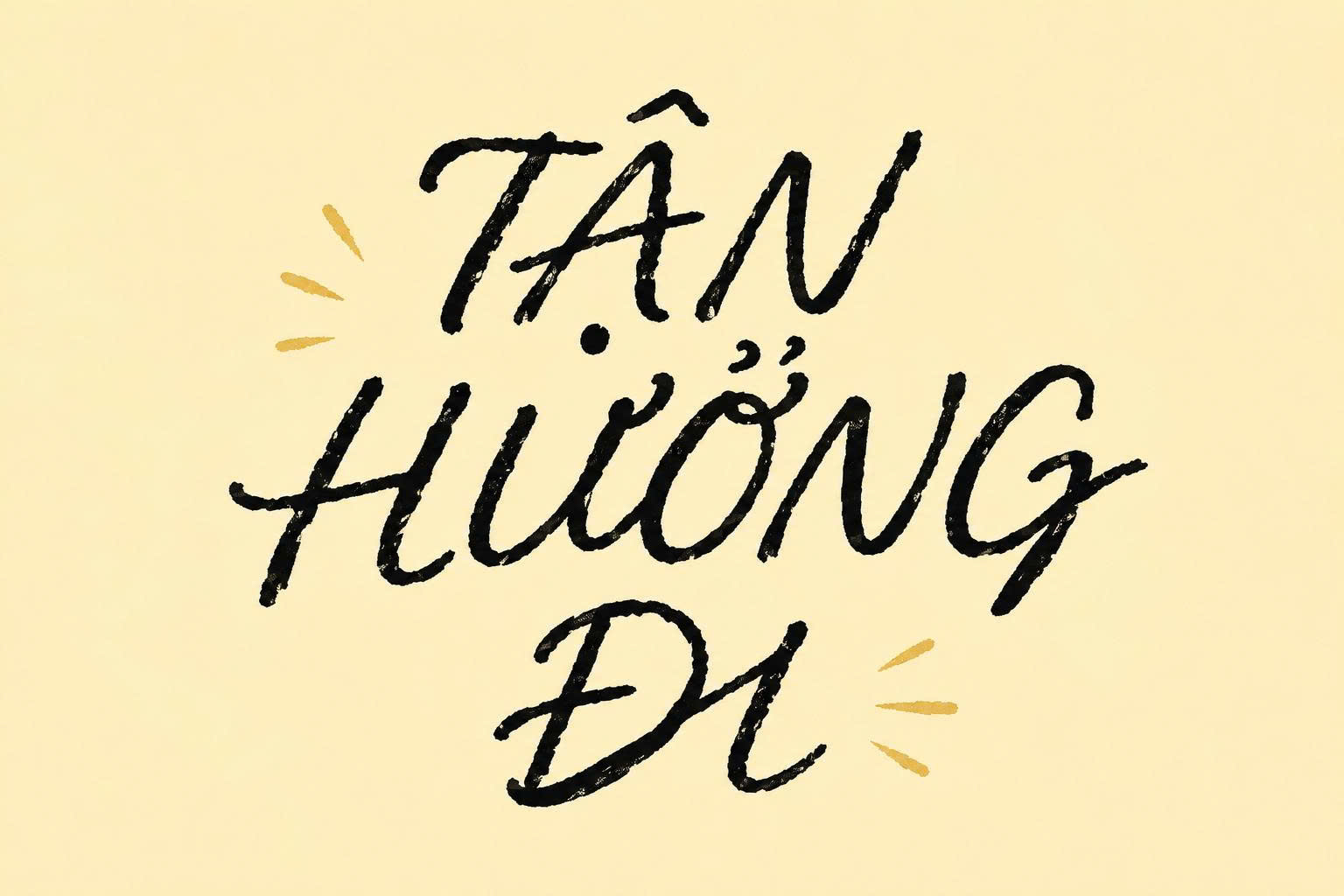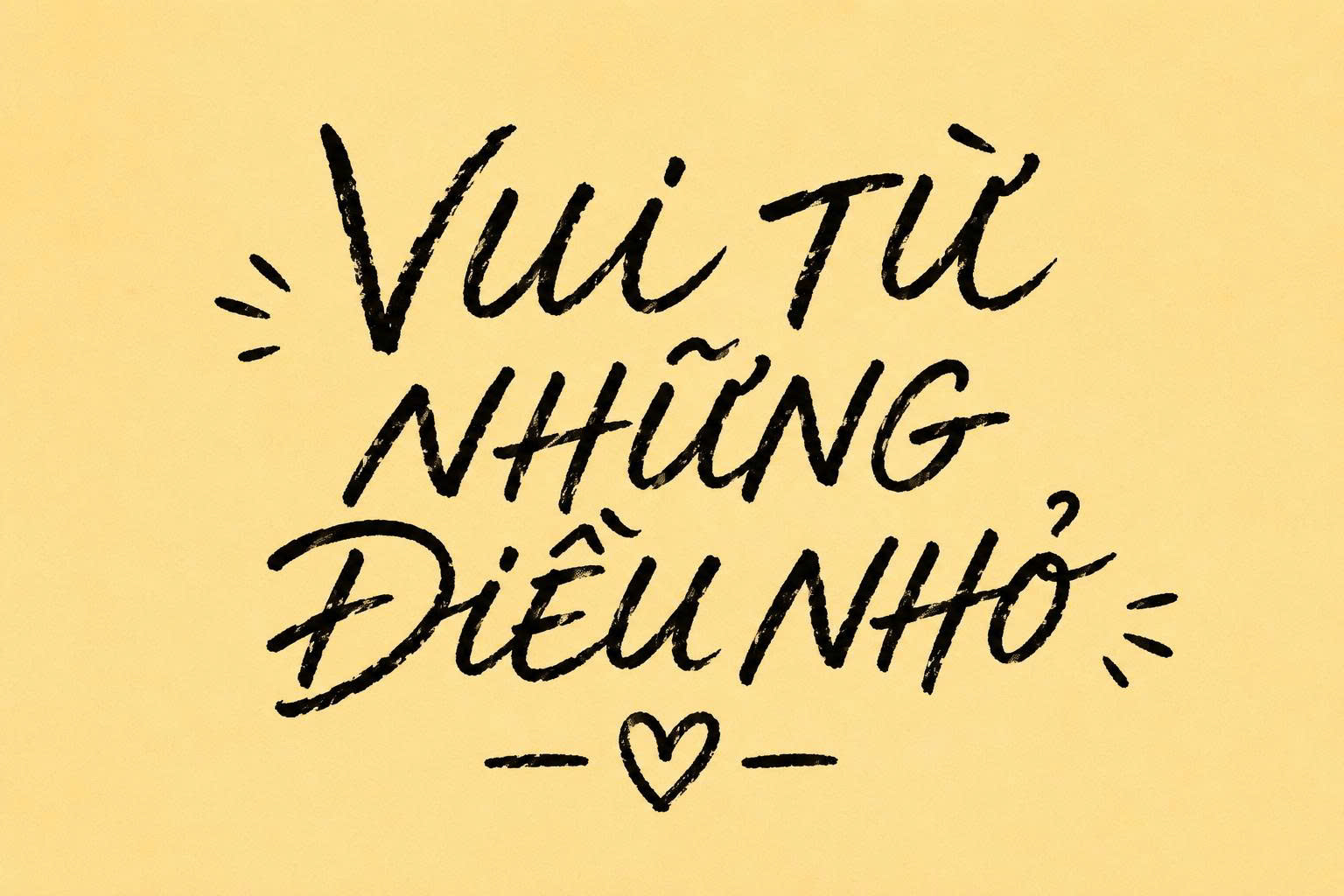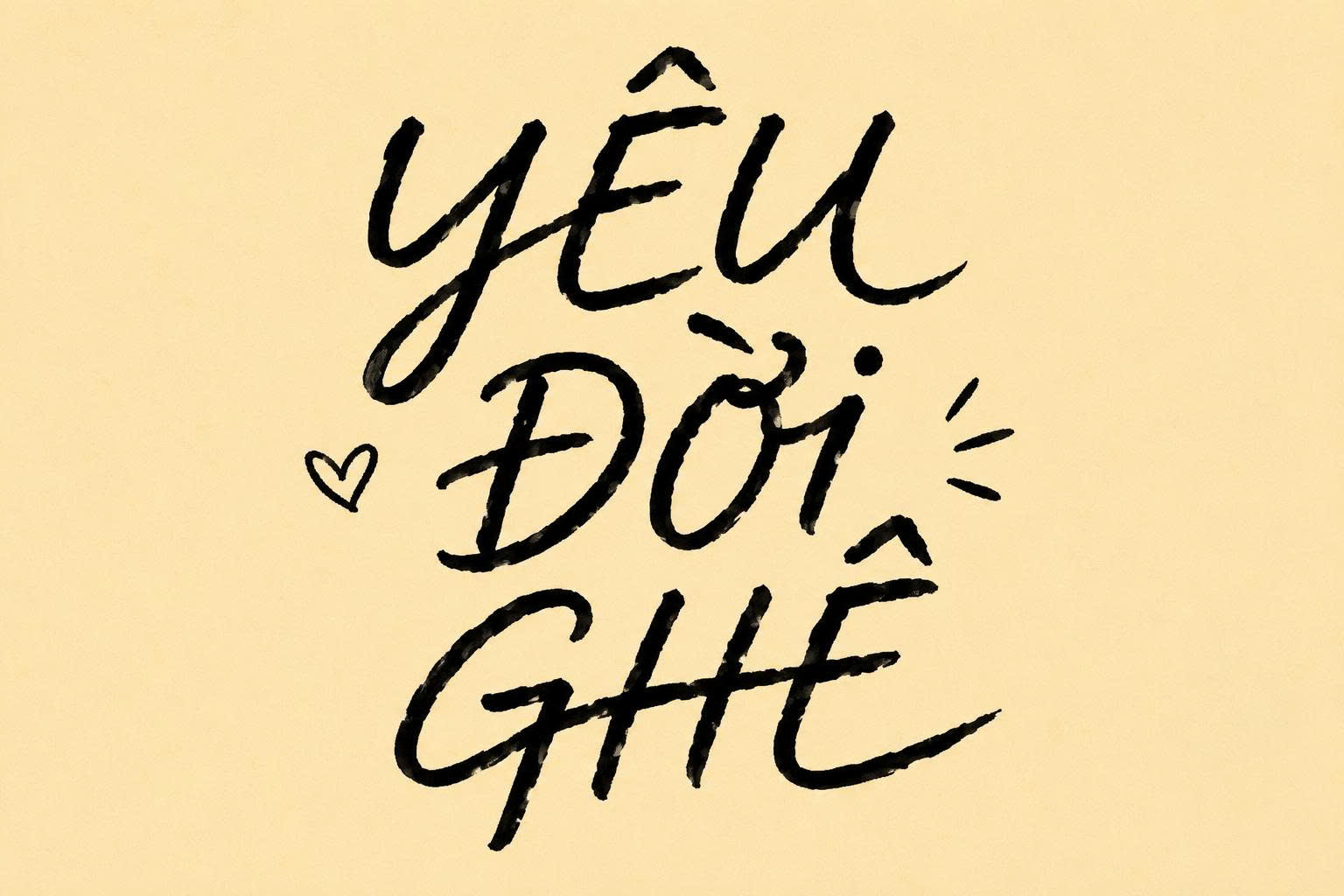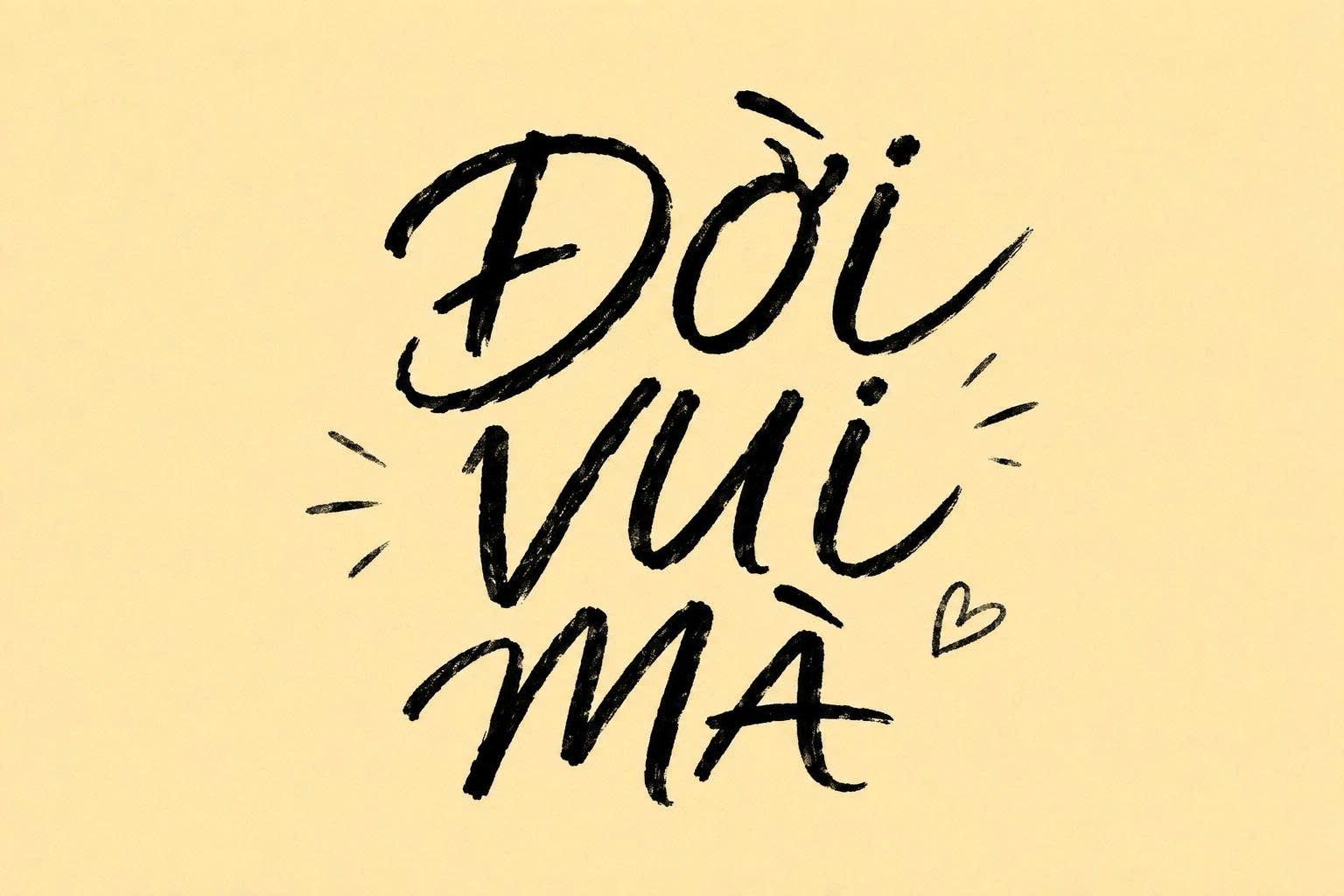
Homemade Apple Font Việt hóa là bộ phông chữ viết tay mang phong cách ngẫu hứng, mô phỏng lại nét chữ viết bằng bút chì hoặc bút sáp trên mặt giấy thô. Với những đường nét mảnh mai, không theo quy chuẩn gò bó, bộ font này mang lại cảm giác vô cùng mộc mạc, chân thực và ấm áp. Doozypack.vn cung cấp link tải font Homemade Apple Việt hóa chuẩn, giúp bạn sở hữu bộ font chữ Homemade Apple tiếng Việt hoàn hảo để thiết kế nhãn mác, thiệp mời và bao bì sản phẩm mà không lo lỗi hiển thị dấu thanh.
Đặc điểm thẩm mỹ của font Homemade Apple Việt hóa
Homemade Apple không chỉ là một phông chữ viết tay đơn thuần, nó chứa đựng cái “hồn” của những bản viết tay thực thụ, gợi nhớ đến những tấm thẻ công thức nấu ăn hay những mẩu giấy nhắn gắn trên tủ lạnh.
Phong cách Handwriting chân thực và gần gũi
Đặc trưng lớn nhất của font Homemade Apple Việt hóa là sự không hoàn hảo một cách cố ý. Các ký tự có kích thước không đồng đều, độ nghiêng thay đổi nhẹ nhàng tạo nên vẻ ngoài tự nhiên như một người đang cầm bút viết trực tiếp lên sản phẩm. Chính sự gần gũi này giúp xóa nhòa khoảng cách giữa thương hiệu và người tiêu dùng.
Nét chữ mảnh mai với độ kết nối ngẫu nhiên
Nét chữ của Homemade Apple khá mảnh, mô phỏng lại áp lực đưa bút nhẹ nhàng. Các chữ cái có sự kết nối một cách phóng khoáng, mang lại nhịp điệu trôi chảy cho dòng văn bản. Khi được Việt hóa tại Doozypack.vn, bộ dấu tiếng Việt được tinh chỉnh để giữ nguyên độ thanh mảnh, đảm bảo không làm khối văn bản bị nặng nề hay rối mắt.
Tại sao nên sử dụng font chữ Homemade Apple tiếng Việt cho bao bì?
Trong ngành in ấn bao bì tại Doozypack.vn, Homemade Apple là “vũ khí” bí mật cho các thương hiệu muốn nhấn mạnh yếu tố thủ công:
- Khẳng định giá trị Handmade: Font chữ này giúp sản phẩm trông như được làm thủ công tại nhà (Home-cooked), gia tăng sự tin tưởng về chất lượng sạch và tự nhiên.
- Xử lý nội dung tiếng Việt mượt mà: Việc sử dụng font Homemade Apple Việt hóa giúp bạn gõ các tên sản phẩm như “Mật ong rừng”, “Mứt dâu tây” hay “Bánh thủ công” một cách chỉn chu, đẹp mắt.
- Tạo điểm nhấn cảm xúc: Nét chữ viết tay luôn mang lại cảm xúc mạnh mẽ hơn các font chữ máy tính khô khan, giúp khách hàng cảm nhận được tâm huyết của người sản xuất.
03 Ứng dụng của font Homemade Apple trong ngành in ấn tại Doozypack.vn
Sự mộc mạc của Homemade Apple khiến nó trở thành “ngôi sao” trên các ấn phẩm bao bì tại Doozypack.vn:
- Nhãn dán hũ thực phẩm: Cực kỳ đẹp khi dùng làm nhãn cho hũ mứt, mật ong, các loại hạt khô hoặc thực phẩm lên men hữu cơ.
- Thiệp cảm ơn (Thank you card): In những lời nhắn nhủ ngắn gọn bằng font Homemade Apple đặt trong hộp hàng tạo nên trải nghiệm mở hộp (unboxing) vô cùng ấm áp.
- Túi giấy Kraft: Nét chữ viết tay màu đen trên nền túi giấy Kraft nâu tạo nên phong cách Vintage, mộc mạc và rất hợp thời.
03 Lưu ý kỹ thuật khi in ấn font chữ viết tay mảnh như Homemade Apple